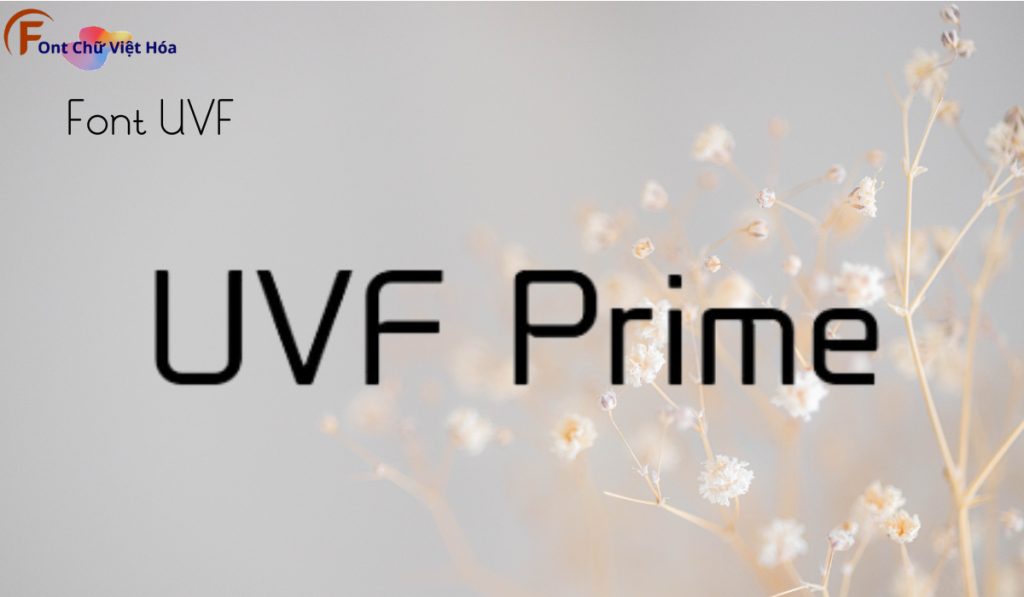
Bộ Font: UVF
UVF Prime Việt Hóa là font sans-serif với các đường nét cá tính và độc đáo, thuộc bộ font UVF. Font này được thiết kế nhằm mục tiêu tạo ra sự rõ ràng và dễ đọc, đặc biệt phù hợp cho các thiết kế như poster, logo, và tiêu đề. Đặc điểm hình dạng của UVF Prime là các đường nét đậm và tỷ lệ chữ cân đối, giúp tối ưu hóa không gian và tạo ấn tượng thị giác mạnh mẽ. Font này cũng đã được Việt hóa, mang đến sự linh hoạt và tiện dụng cho các dự án thiết kế bằng tiếng Việt, giúp người dùng dễ dàng tiếp cận và sử dụng.